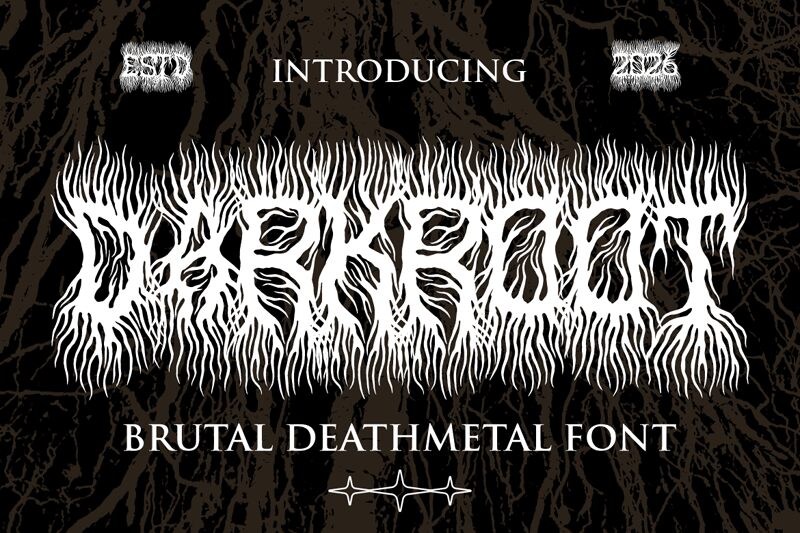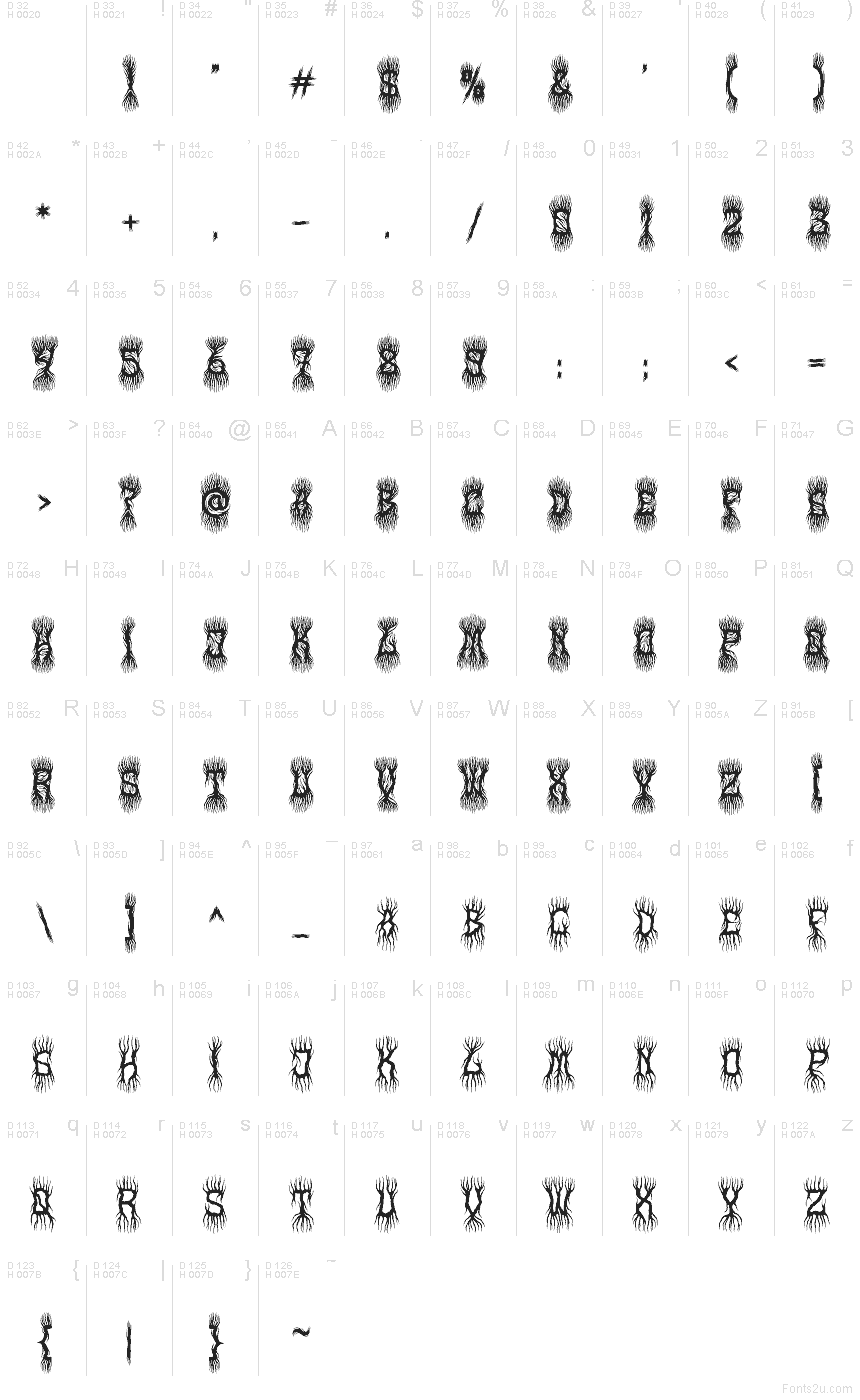
Dark Root
Dark Root da Shanaf Studio é uma fonte display gótica gratuita com uma estética black metal e letras que parecem criar raízes emaranhadas. As formas mantêm-se como silhuetas arrojadas, mas cada extremidade desfaz-se num crescimento ramificado, conferindo à fonte um ambiente húmido, selvagem e underground.
Isto torna esta fonte gratuita uma escolha forte para capas de álbuns, cartazes de terror, folhetos de festivais, títulos de jogos e merchandising onde o lettering deve parecer vivo e invasivo. Funciona melhor em nomes curtos, legendas e cabeçalhos de estilo logótipo, porque os traços semelhantes a raízes criam uma atmosfera imediata e transmitem o texto com uma ameaça crua e orgânica.